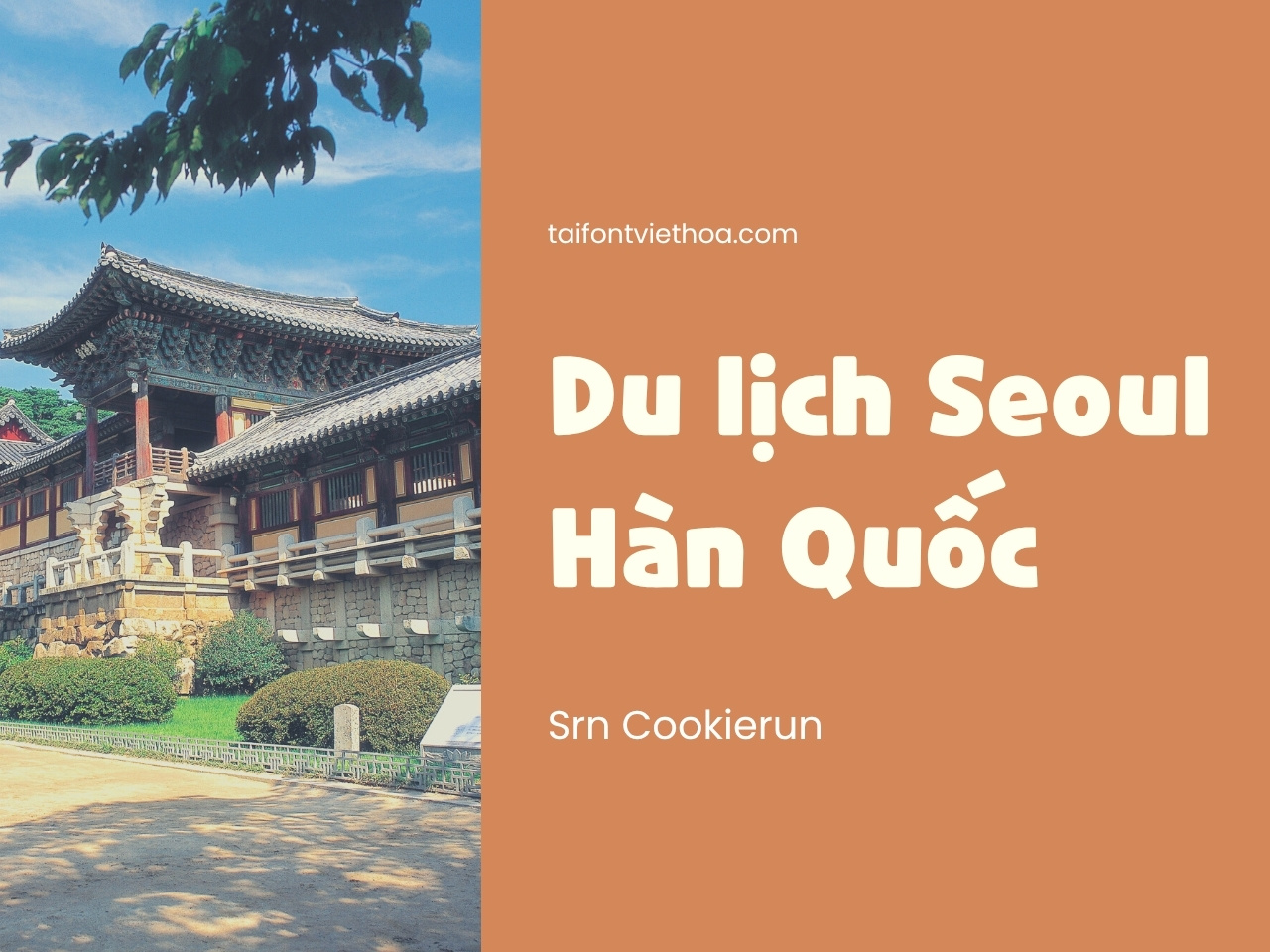
Font việt hóa Srn Cookierun Có Tiếng Hàn
Giới thiệu về font Srn Cookierun – Có tiếng Hàn
Srn Cookierun là một font chữ đáng yêu, vui nhộn, được phát triển dựa trên hệ thống font của tựa game nổi tiếng Cookie Run đến từ Hàn Quốc. Font mang phong cách hoạt hình đặc trưng với hình dáng tròn trịa, đáng yêu, tạo cảm giác thân thiện và dễ tiếp cận. Phiên bản Việt hóa đã được hoàn thiện để hỗ trợ đầy đủ tiếng Việt với hệ dấu rõ ràng và cân đối, đồng thời giữ nguyên khả năng hiển thị tiếng Hàn (Hangul). Ngoài tiếng Việt và tiếng Hàn, font cũng hỗ trợ nhiều ngôn ngữ khác dựa trên hệ mã Unicode và Latin mở rộng. Font đã được taifontviethoa.com chọn lọc và kiểm thử thực tế, rất phù hợp với các dự án thiết kế trẻ em, giáo dục hoặc game.
Đặc điểm thiết kế và ứng dụng của Srn Cookierun
Font sở hữu đường nét bo tròn, nét chữ to, dày và có độ mềm mại cao, giúp tạo sự nổi bật trong các thiết kế mang tính vui vẻ hoặc cần thu hút trẻ nhỏ. Các ký tự được thiết kế hài hước, mang cảm giác hoạt hình và dễ thương. Phần tiếng Hàn tích hợp giúp font này có thể sử dụng cho các thiết kế song ngữ Việt–Hàn một cách thuận tiện.
Font Cookierun đặc biệt phù hợp trong các thiết kế banner, tiêu đề game, giao diện ứng dụng giáo dục, sách thiếu nhi, bao bì đồ chơi, quảng cáo sản phẩm trẻ em hoặc các sự kiện theo phong cách Hàn Quốc. Ngành nghề lý tưởng: giáo dục mầm non, thiết kế game, truyền thông trẻ em, sản phẩm tiêu dùng cho thiếu nhi, tổ chức sự kiện văn hóa Hàn – Việt.